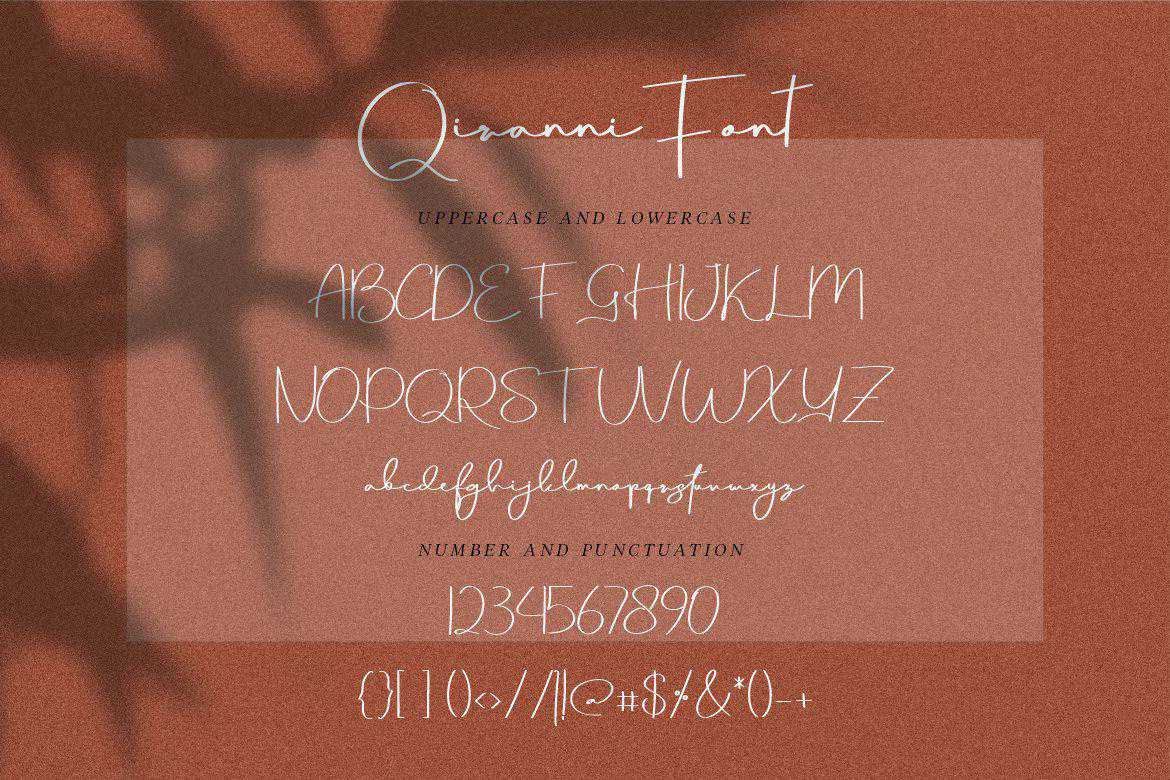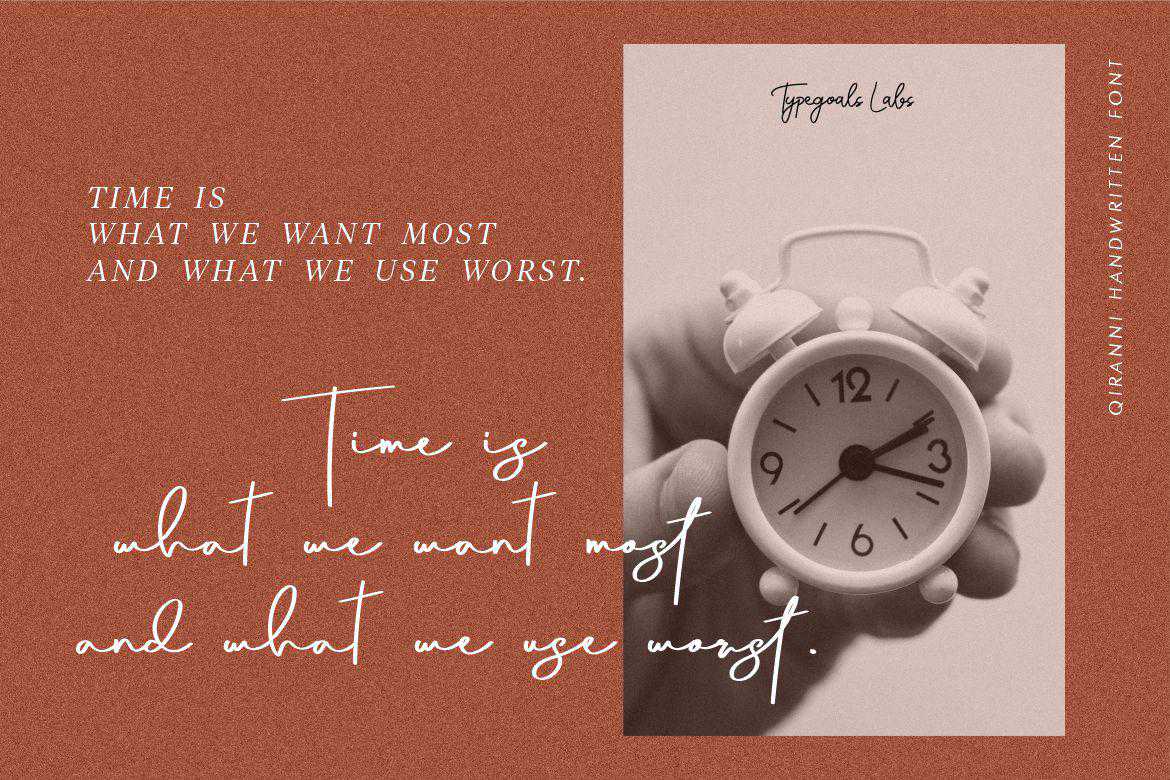
QiranNifontScriptFont是一款现代的书写、美丽的、浪漫的剪贴画字体。它的特点是美观、连字和涂鸦。这款字体美观大方,非常适合于书写项目,如增加灵感、美化艺术、吸引眼球的社交主题、引文、剪贴画和更多。QiranNifontScriptFont是一款现代的书写字体,美丽和浪漫的彩绘字体。它的特点是立体感、连字和涂鸦。这种字体美丽而优雅,非常适合于书写项目,如增加灵感、美化艺术、吸引眼球的社交主题、引用、剪贴画等等。